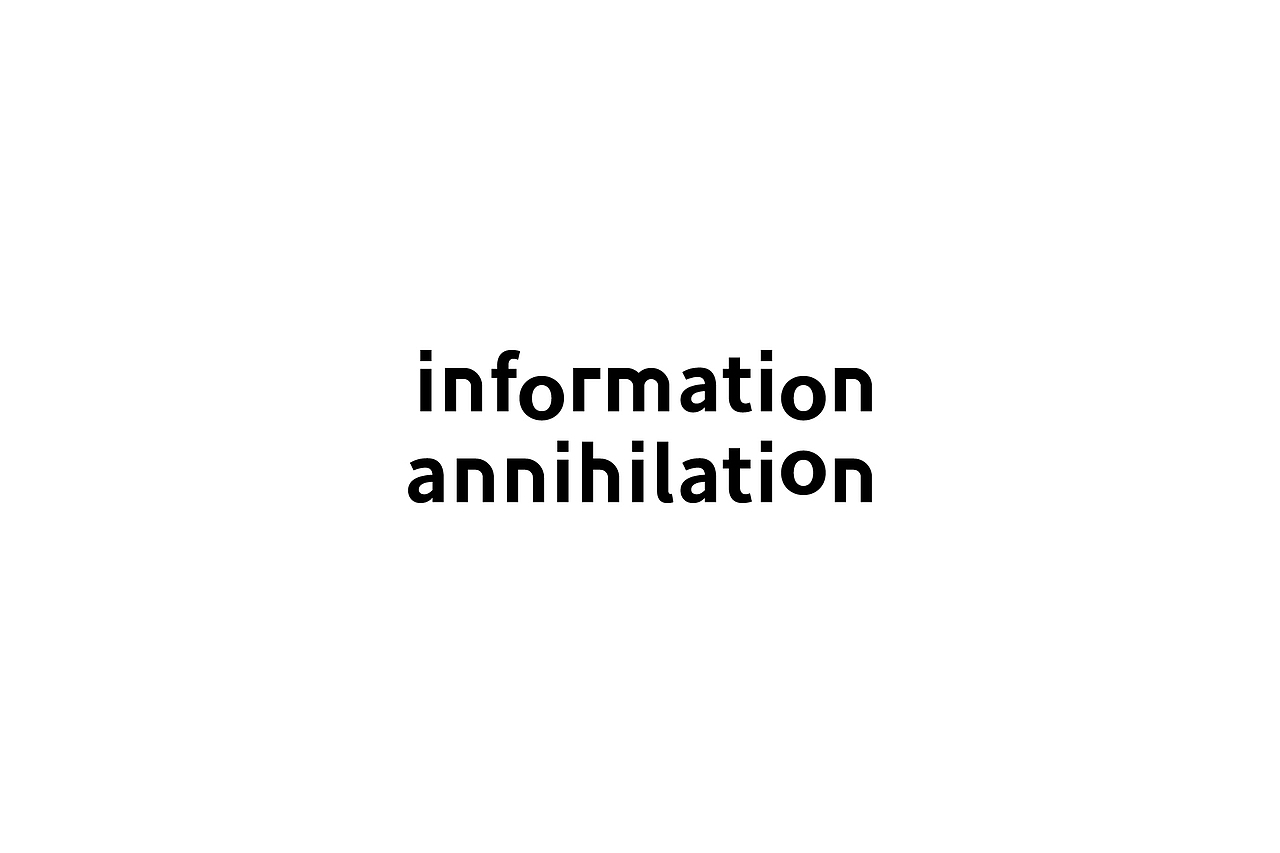
信息湮没|字体设计
第一周主题:『信息湮没』
通过理解,“信息湮没”气质现代并带有一丝未来的颓废感。身处于信息时代的我们对于过度饱和的信息都会有自己的体会。面对过度饱和的信息,我们对于信息内容的理解越来越流于表面,对于信息内容的真实面目也越来越模糊,浏览、跳读、为消除小红点的点开关闭标记已读成为我们日常对待信息的方式。我们“淹没”于信息中,信息也“湮没”于我们当中。
这种模糊中带有外轮廓的感受触发我此次采用外文中用的方式设计字体,在识别无碍的基础上增加字体的趣味性,也增加那一丝未来的颓废感。等线的创意字形设计形式让字体在排列中形成pattern,达成“我们淹没于信息,信息也湮没于我们”的感受。